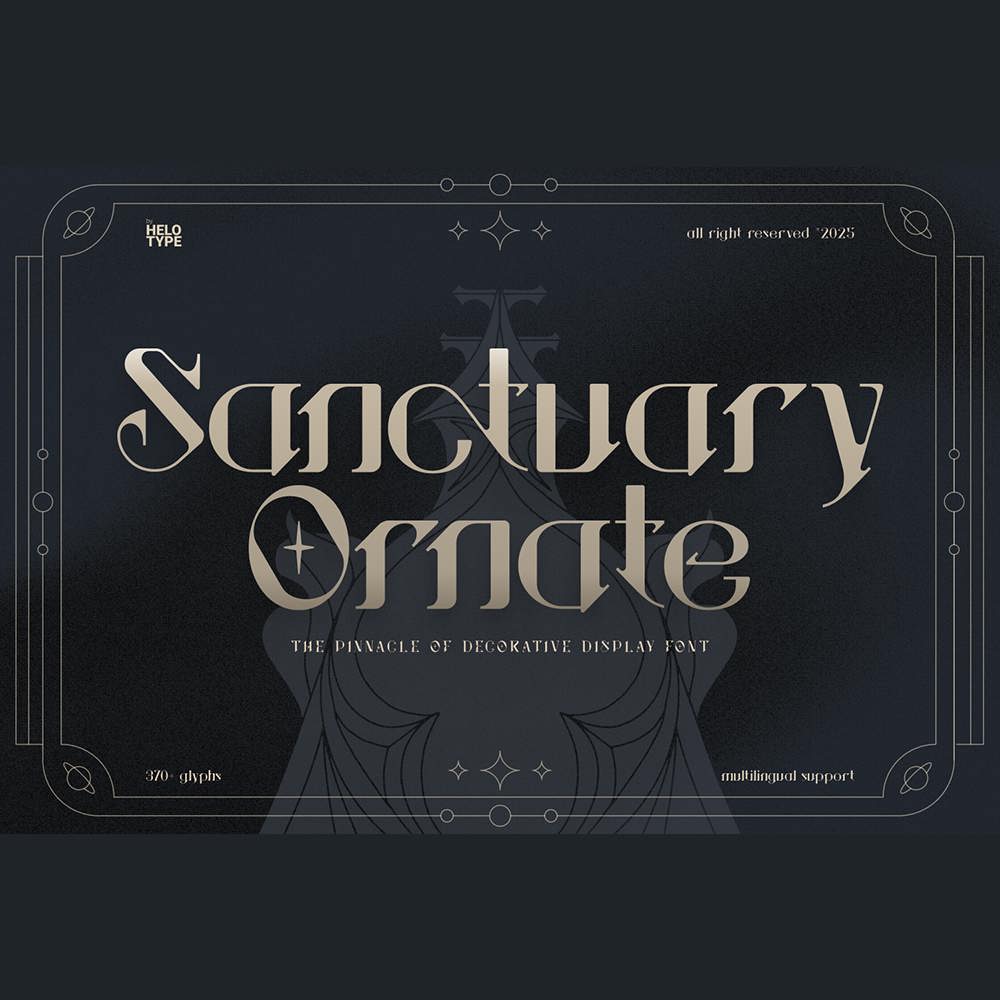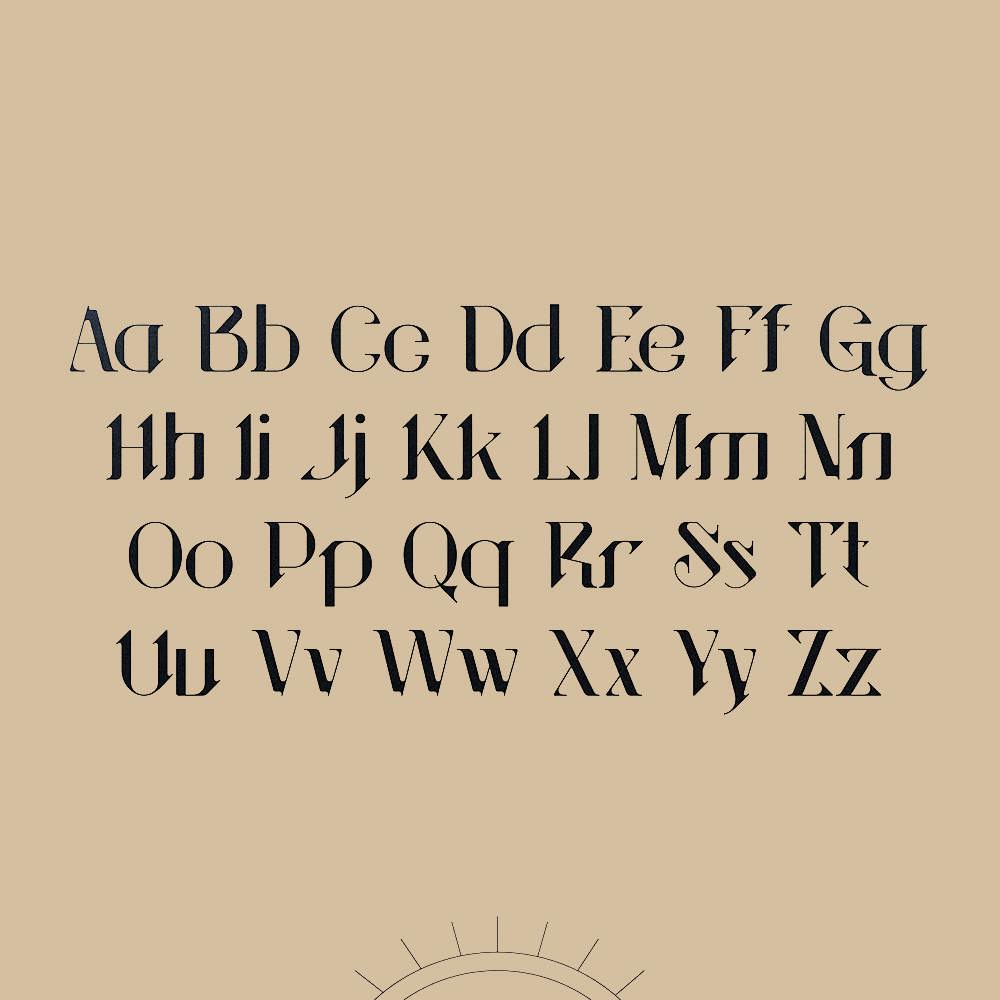
فونت پرمیوم و انگلیسی Sanctuary Ornate Font یک فونت نمایشی باشکوه است که با دقت ساخته شده تا پروژههای شما را با ظرافتی بینظیر و حال و هوایی از تجمل بیزمان پر کند. این فونت که برای برندسازی سطح بالا، طرحبندیهای سرمقالهای پیچیده، جلدهای کتاب دلربا و پروژههای بازی ایدهآل است، نوید میدهد که آثار شما را از زیبایی به فراموشنشدنی ارتقا دهد. اوج طراحی تزئینی را کشف کنید و به کار خود شکوهی را که شایسته آن است، ببخشید.
مزایای استفاده از فونت لاتین Sanctuary Ornate چیست؟